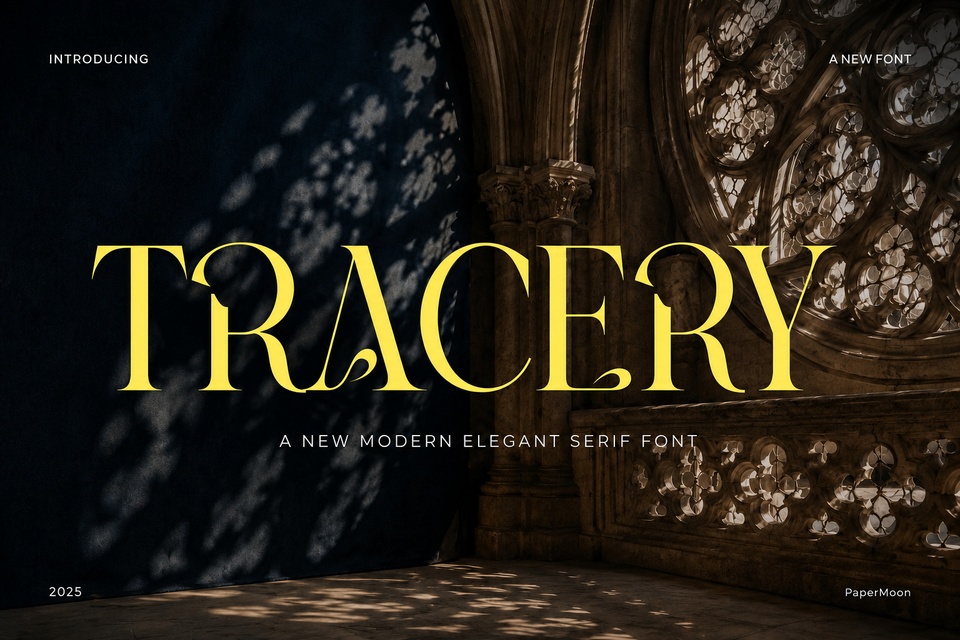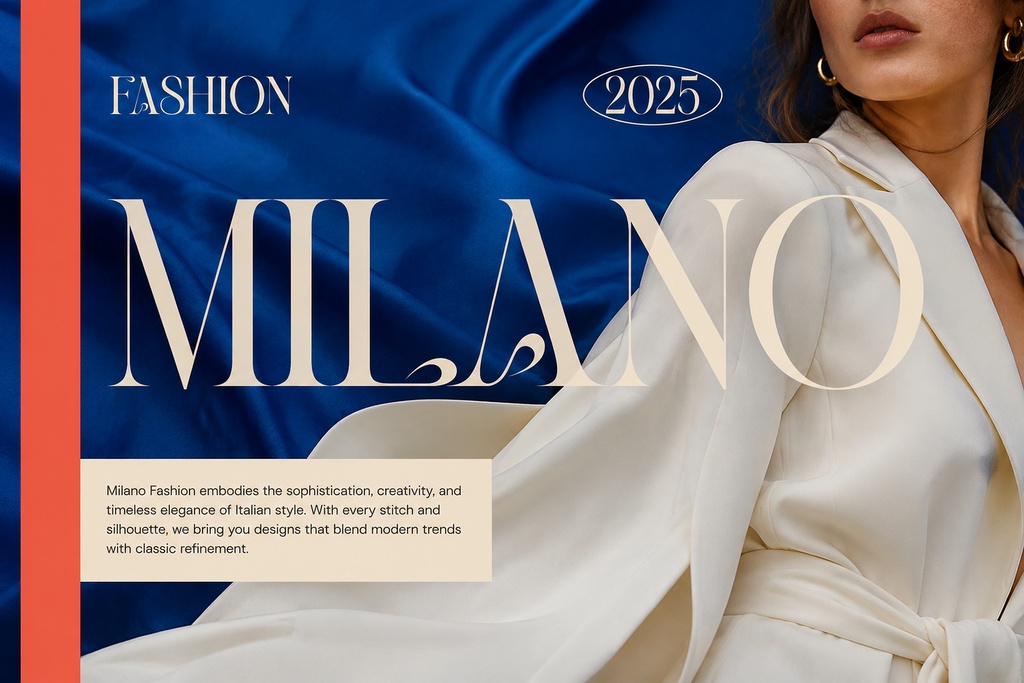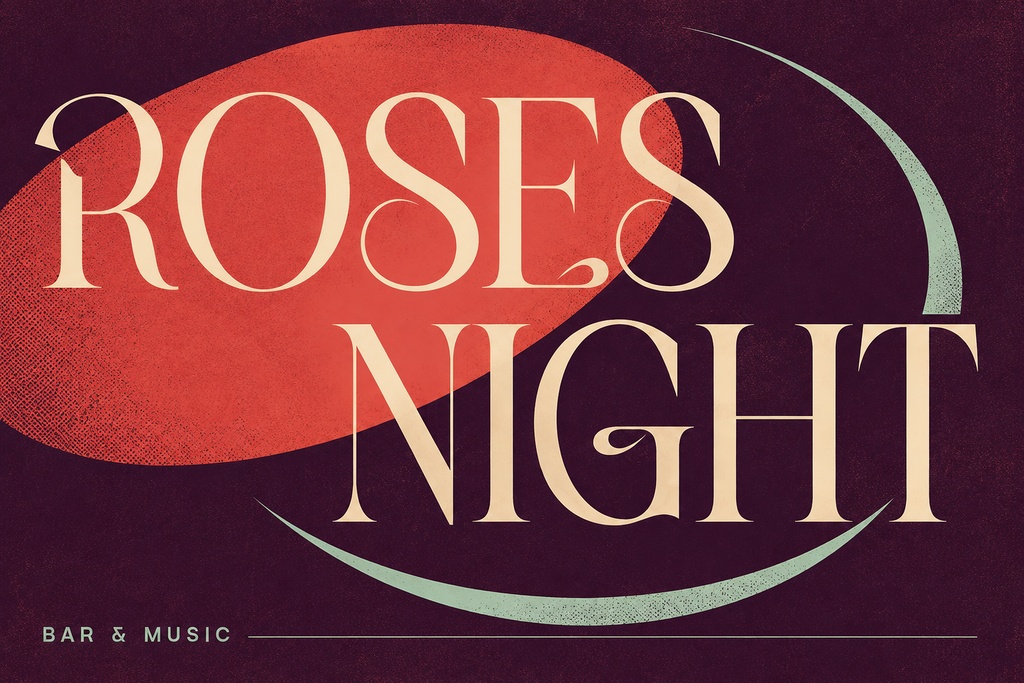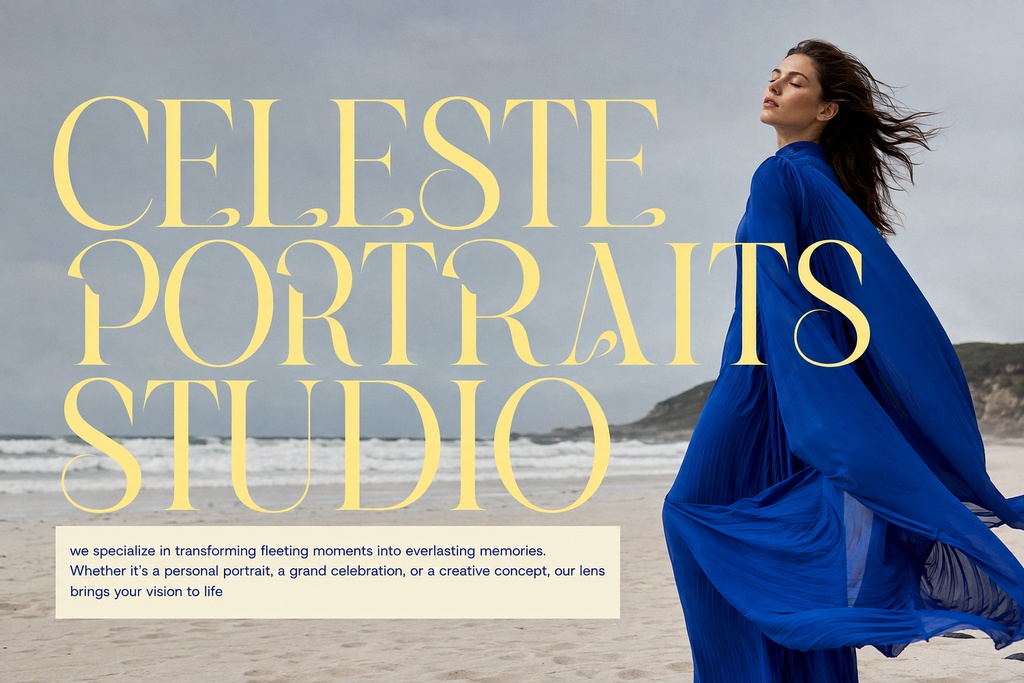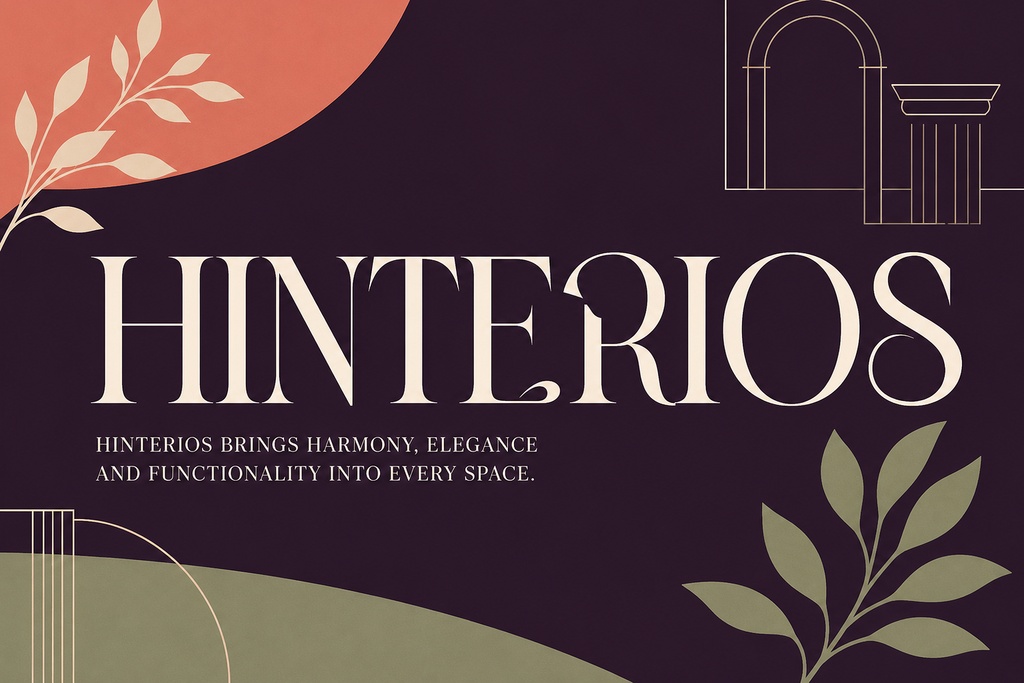
Tracery - ブランディングとエディトリアルデザインに最適なスタイリッシュなセリフフォント
Traceryは、ディスプレイ・タイポグラフィに現代的で洗練された印象をもたらす、スタイリッシュなセリフフォントです。クラシックなセリフ構造と、モダンで表情豊かなレターフォームを融合させることで、エレガントなセリフ書体ならではの上品さを保ちながら、フレッシュで親しみやすい雰囲気を演出します。温かみと読みやすさを損なうことなく、個性的で高級感のあるタイポグラフィを求めるデザイナーのために作られた、洗練されたセリフフォントです。Traceryはディスプレイ向けのセリフフォントとしてデザインされており、大きなサイズで使用した際にその魅力を最大限に発揮します。見出し、ロゴ、プレミアム印刷物などに適しており、バランスよく設計された文字形状によって、補助テキストにも優雅さと高い可読性をもたらします。 **収録内容:** Traceryは、現代的なセリフフォントとして単一のRegularスタイルで提供されます。パッケージには、デスクトップ制作向けのOTFおよびTTFフォントに加え、デジタルプロジェクト向けのWebフォントWOFFファイルが含まれています。精巧なリガチャと丁寧にデザインされた代替文字により、あらゆるプロジェクトにさらなるクリエイティブな魅力を加えることができます。Traceryは、OpenType GSUB置換機能とGPOSカーニングを搭載した洗練されたセリフフォントで、OpenTypeに対応するアプリケーション上では文字ペアを美しく均整の取れた状態で配置できます。基本的な文字、数字、句読点に加え、フランス語、ドイツ語、スペイン語など、一般的な西ヨーロッパ言語の文章に対応するアクセント付き文字も収録されています。ファイルはWindowsとMacの両方にスムーズにインストールでき、1回のダウンロードでPCとMacの両方に対応するセリフフォントとして使用できます。 **主な特徴:** 精巧なリガチャと丁寧に作り込まれた代替文字が、ロゴタイプや見出しにハンドメイドのような仕上がりを与えます。エディトリアル向けのセリフフォントとして、Traceryは雑誌の見開きやレイアウトに洗練された編集デザインの雰囲気を加えます。現代的なセリフフォントらしいプロポーションにより、クリーンなサンセリフ体の補助テキストとも美しく組み合わせることができます。OpenTypeリガチャと代替文字は特に魅力的な機能で、プロフェッショナルなレイアウトに必要な数字、句読点、アクセント付きグリフも幅広く収録されています。 **用途:** Traceryは、高級ブランドのブランディング、洗練されたロゴデザインやロゴタイプ、プレミアムパッケージデザイン、高級感のあるパンフレットの表紙など、さまざまなデザインプロジェクトに活用できます。ファッション、フード、ブティック、不動産などのWebサイトにも適した洗練されたタイポグラフィであり、ウェディング招待状、ブティックのブランディング、ファッションブランドのデザイン、雑誌レイアウトにも美しく馴染みます。広告、マーケティングキャンペーン、ポスター、ステーショナリー、特別イベントの招待状などにも、Traceryのエレガントで現代的な個性を活かすことができます。高級ブランドのアイデンティティを構築するセリフフォントとして、パッケージラベル、レストランメニュー、ブランドツールにも上品な印象を加えます。また、プレミアム商品パッケージや、洗練された不動産広告・プロパティキャンペーンにも適した信頼性の高いセリフフォントです。 **互換性:** 収録されているOTF、TTF、WOFF、WOFF2フォントにより、デスクトップとWebの両方の制作環境に対応しています。WOFFファイルはWebサイトで直接使用でき、デスクトップ用フォントはAdobe Illustrator、Adobe Photoshop、InDesign、Canvaなどの各種デザインソフトウェアで使用できます。洗練された広告キャンペーン向けフォントとして、Traceryは印刷物、Web、ソーシャルメディアを通して統一感のある高級感のあるタイポグラフィを実現します。 **ライセンス:** 商用デザインでの使用には、Cubebrush Commercial Licenseの利用を推奨します。ただし、お客様のプロジェクトに必要となるその他の権利や許可に代わるものではありません。個人利用および非商用利用の場合は、Basic Licenseをご利用ください。購入または公開する前に、Cubebrushの商品エディターに表示されているライセンスオプションをご確認ください。 Traceryで、次のブランディング、エディトリアル、パッケージ、招待状デザインに、自然でエレガントな魅力を加えてみませんか。